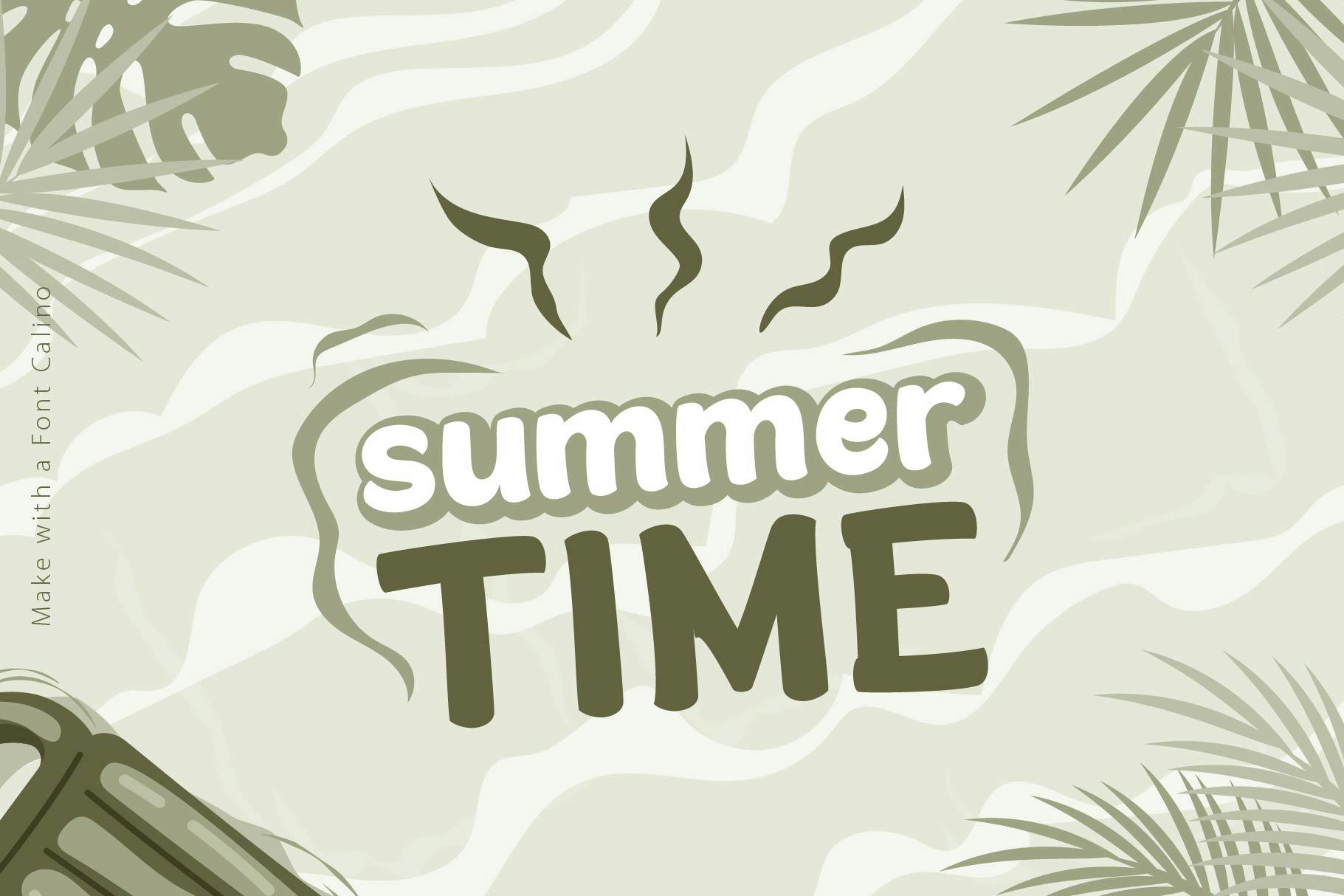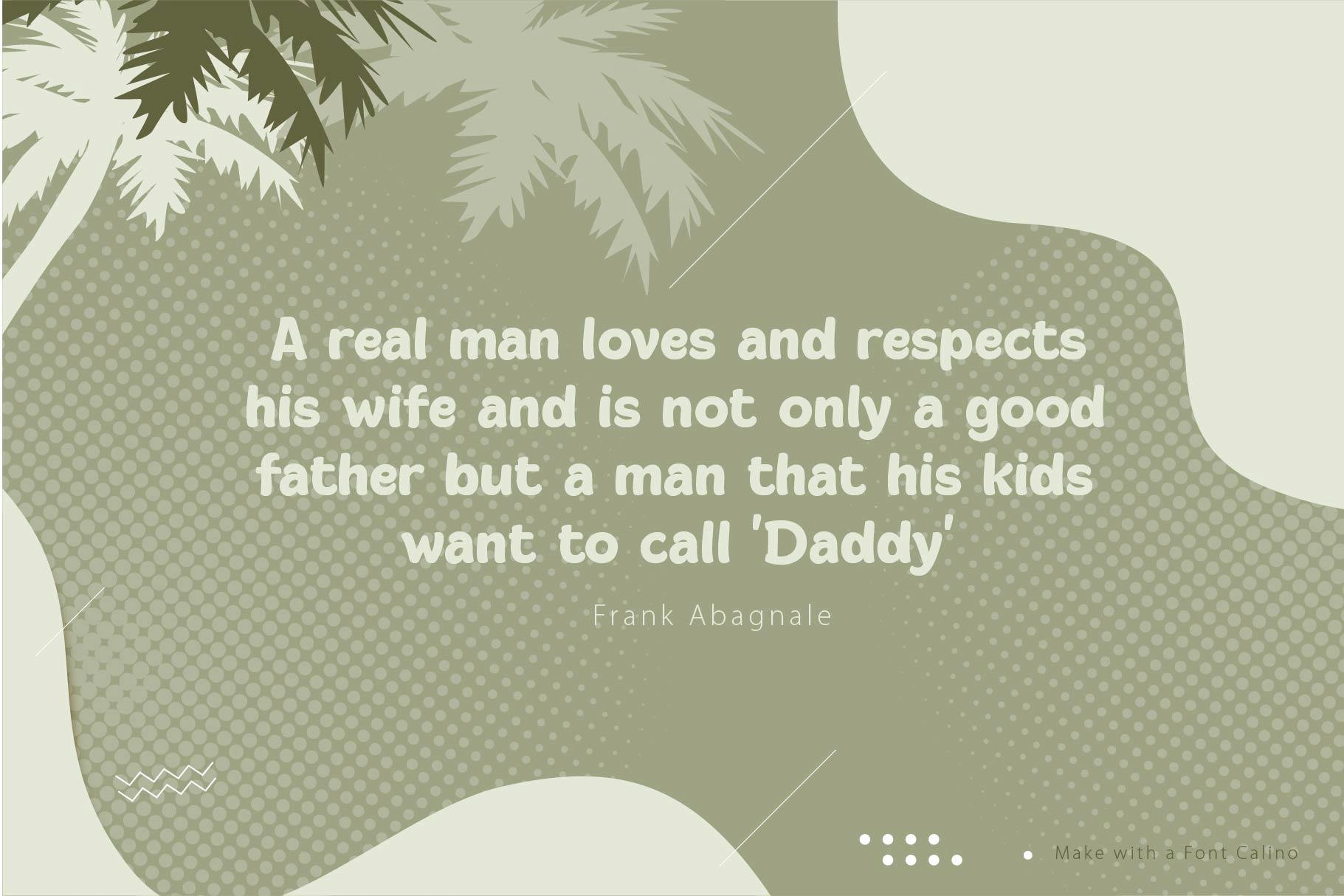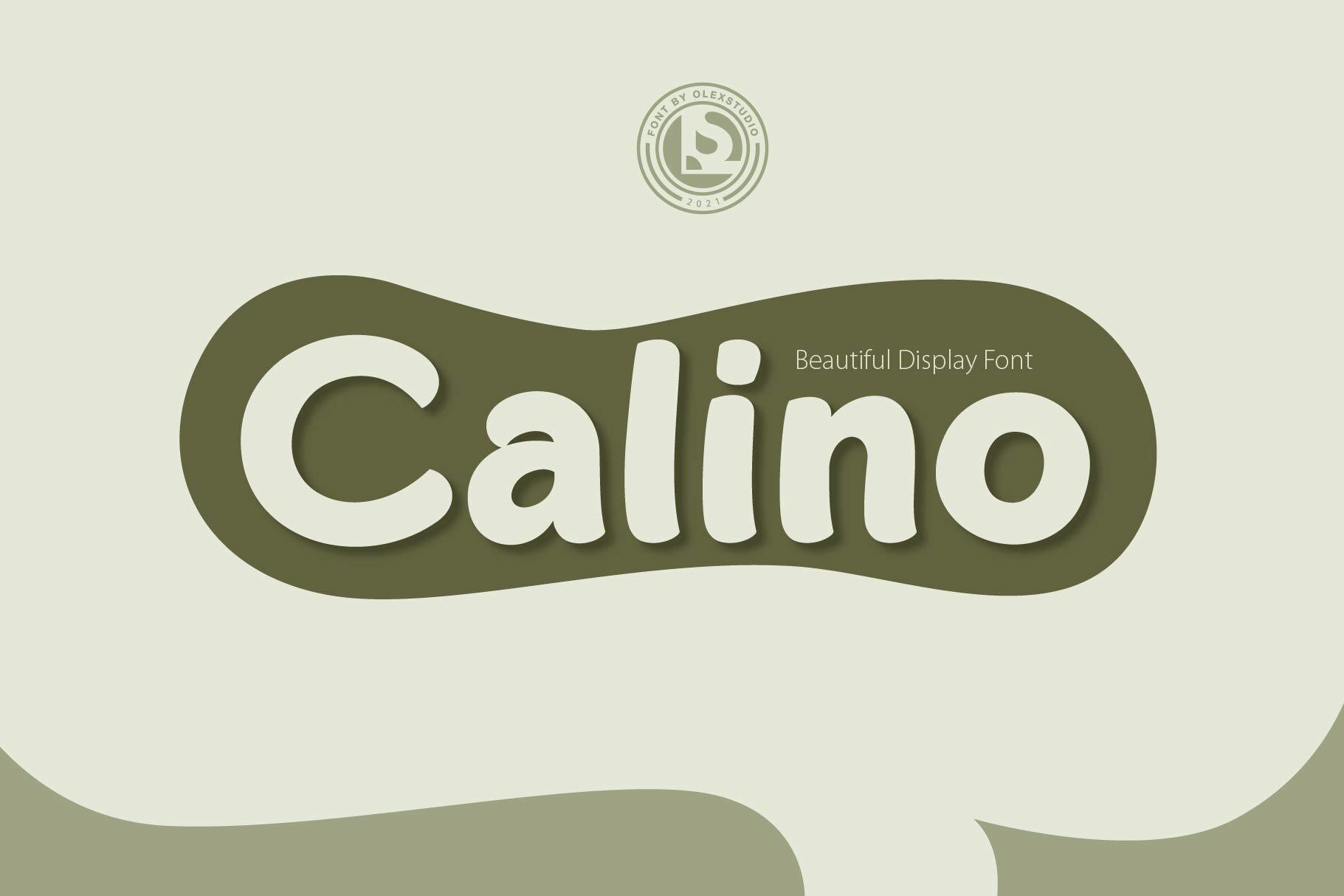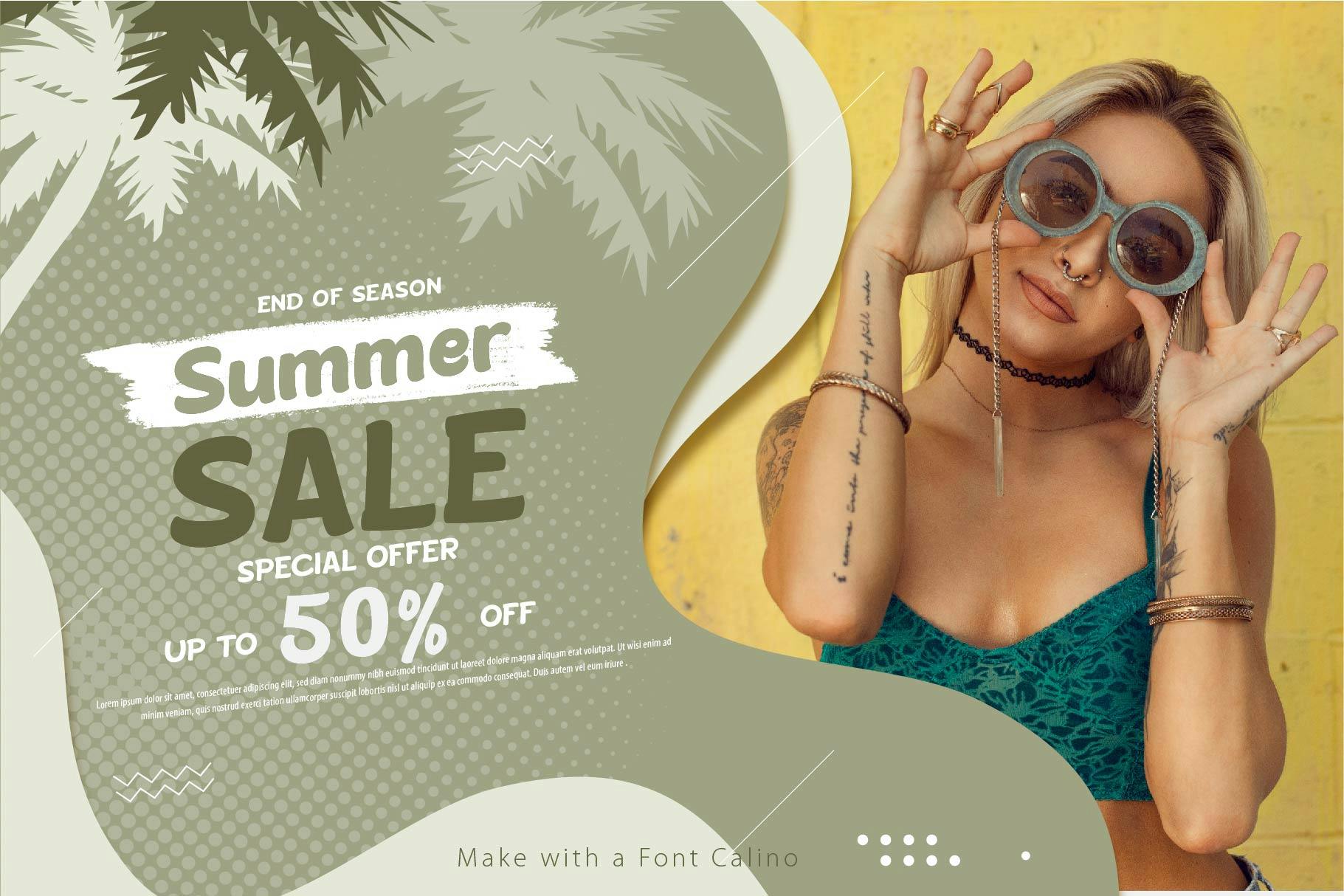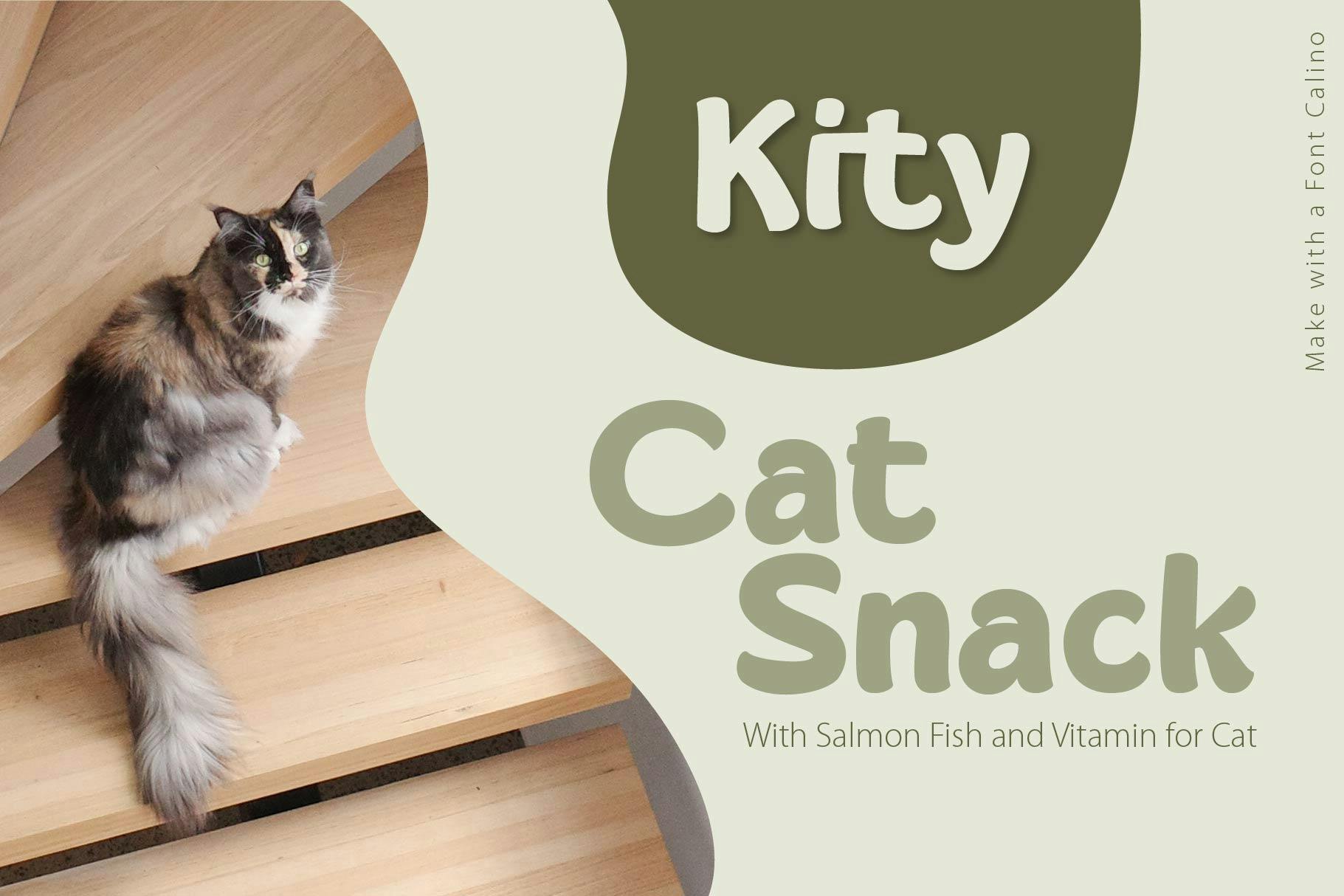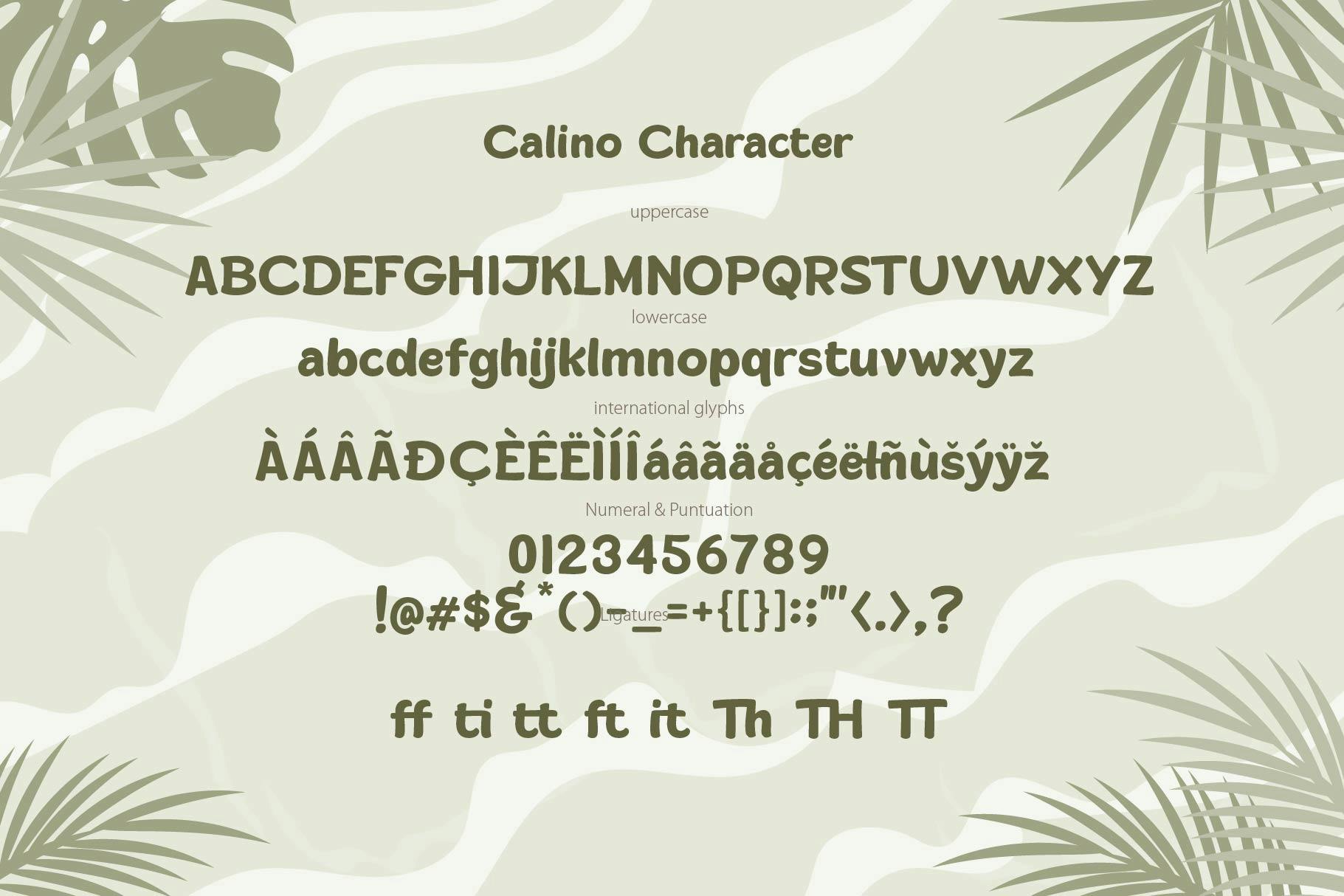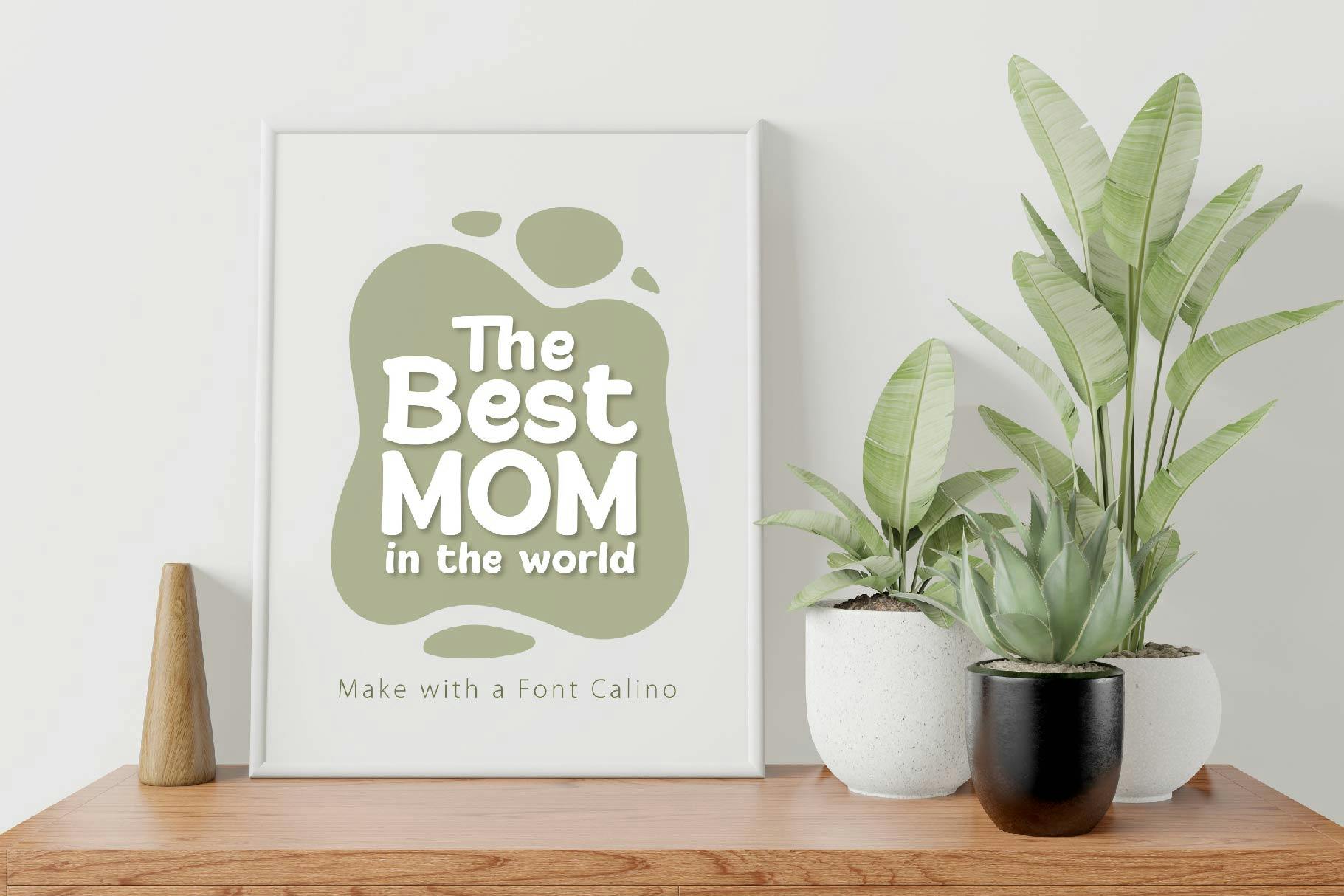
فونت نمایش CALINO در تمام طراحیهای شما، از جمله دعوتنامهها، طراحی پوستر، طراحی کتاب، مواد برندینگ، لوگوها، تیشرتها و سایر پروژهها فوقالعاده به نظر میرسد.
فونت CALINO شامل کاراکترهای استاندارد، حروف کوچک و بزرگ، اعداد، نشانهگذاری، ترکیبنویسی و گلیفهای بینالمللی میباشد.